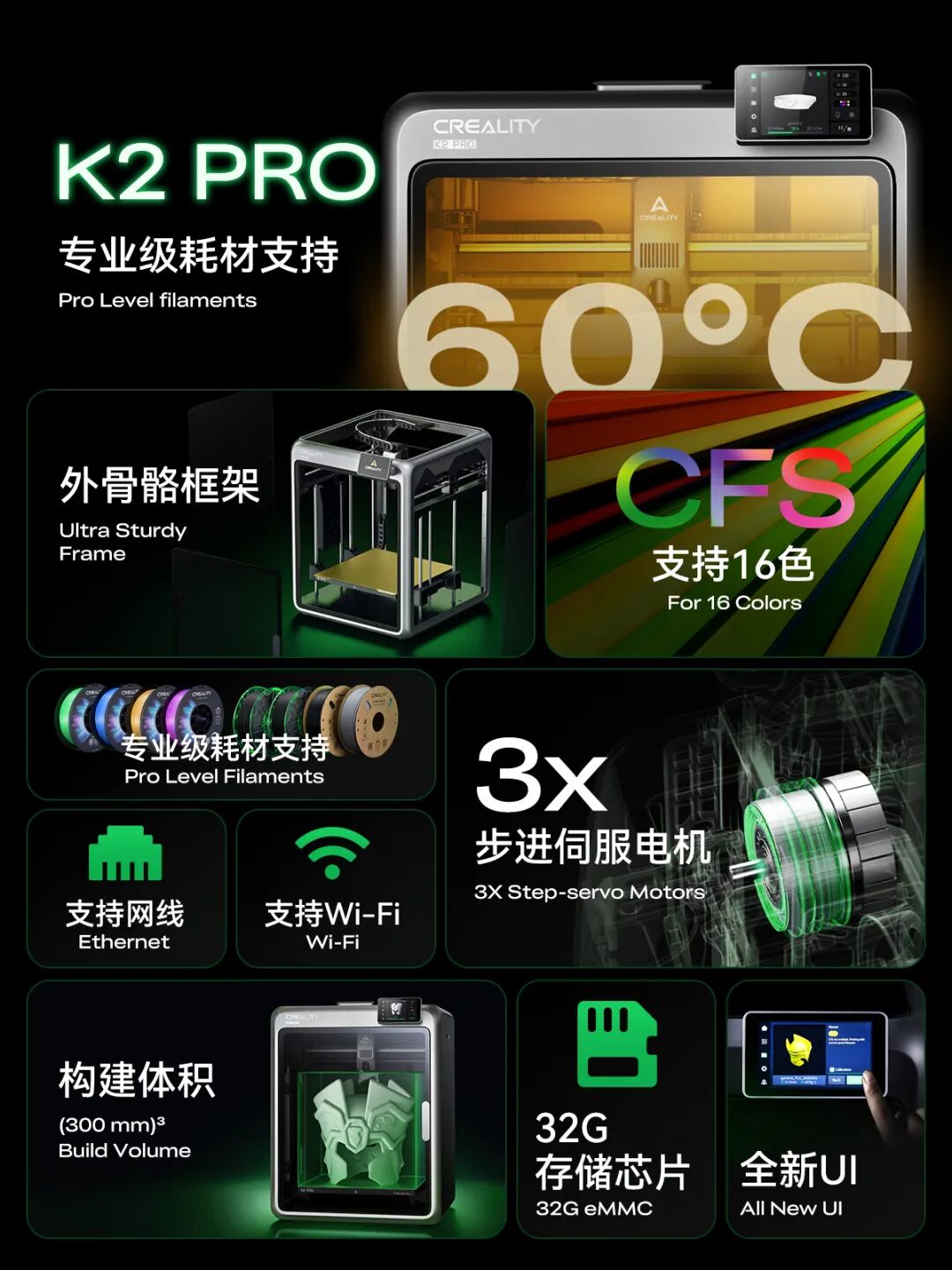
2025年4月9日,创想三维迎来十一周年庆典暨春季新品发布会,以“TO MAKERS BY MAKERS”为主题,携多款新品亮相,并正式发布与方正字库联合打造的 Creality Sans 全新品牌定制西文字体。CrealitySans 以“科技基因”为核心,将品牌对精密工程的追求凝练为可感知的视觉符号,打造品牌视觉统一化。
CrealitySans 应用展示
作为全球领先的3D打印品牌,创想三维始终秉持以科技的力量创造更加美好的世界,让千家万户享受3D打印科技带来的乐趣的品牌使命,致力于将先进的增材制造技术带给更广泛的用户。无论是专业工程师亦或是个人创客,创想三维都希望每一位用户都能将创意转化为现实。这种兼具精密可靠与创新科技的品牌特质,也成为CrealitySans 字体设计的核心方向。
在风格上,CrealitySans 延续了经典Grotesque字体家族的高可读性与结构稳定性,并融入3D打印技术的精密感与现代设计的视觉张力,构建出专属于创想三维的品牌语言。无论是在产品标识、宣传物料,还是产品本体上,CrealitySans 都能精准传递品牌信息,确保视觉表达的统一性和专业度。
方正字库设计团队以创想三维断突破的技术实力和对工艺美学的极致追求为基础,赋予了CrealitySans 字体独特的内涵与辨识度,该字体不仅是品牌精神在视觉传达上的延伸,也是字体设计与品牌理念深度融合的呈现。
CrealitySans 笔画中精心设计的“油墨陷阱”以锐利的几何切割,呼应了3D打印表面的复杂细节,注入了一种独特的“机器视觉”。
作为品牌定制视觉符号,CrealitySans 与创想三维LOGO的断笔细节呼应呈现和斜切元素完美呼应,打破常规并赋予字体向前的速度意象,统一视觉表达效果,强化品牌的科技感。
CrealitySans 断笔设计
CrealitySans 斜切设计
CrealitySans 拥有三款字重,旨在优化统一品牌视觉,用于品牌宣发、产品展示等多场景,确保信息的清晰传达。
方正字库此次与创想三维的携手,旨在共同打造3D打印行业专用定制西文字体。CrealitySans 的推出不仅是技术创新与视觉艺术的完美结合,更是将创想三维品牌理念的视觉语言展现。未来,CrealitySans 将持续助力创想三维,以更加精准与创新的品牌语言,与用户共同书写3D打印的新篇章。